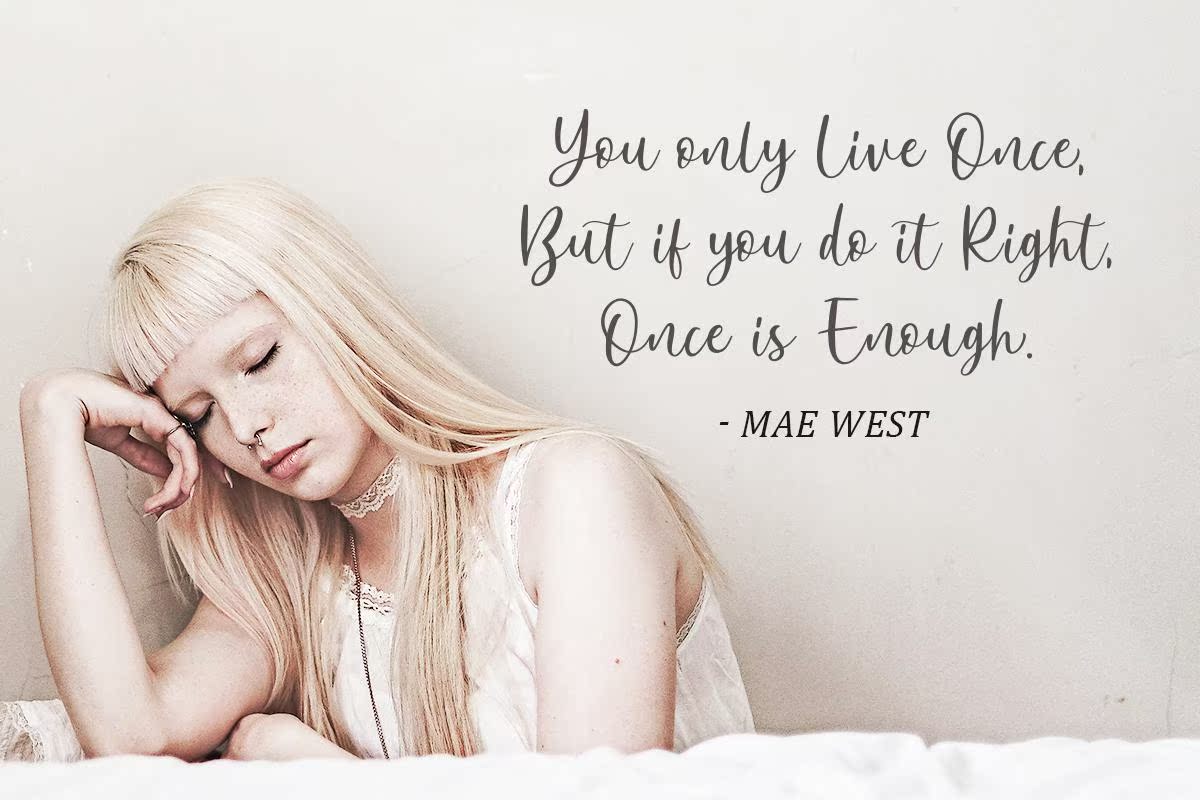
Anjani,一种给人以强烈感觉的现代拼音脚本。自然手写脚本适用于需要头条、标识、服装、邀请、品牌、包装、广告等字体的用户。这种字体包括大写、小写、标点符号、符号和数字、文体设置替代、连字等,支持多语言和首字母编码。Anjani,一种给人以强烈感觉的现代拼音脚本。自然手写脚本适用于需要头条、标识、服装、邀请、品牌、包装、广告等字体的用户。这种字体包括大写、小写、标点符号、符号和数字、文体设置交替、连字等,支持多种语言和可读编码。